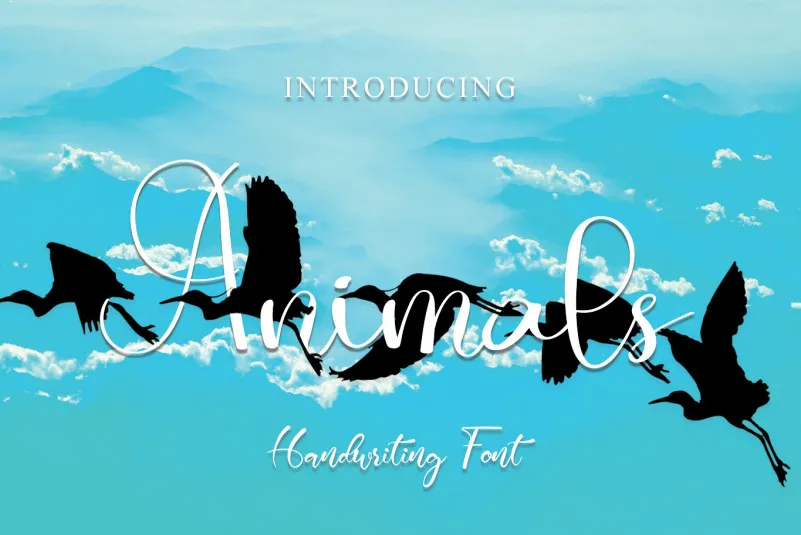
Esta é uma fonte tipo script que se destaca pela sua elegância e detalhe. Ela foi meticulosamente criada para tornar qualquer projeto mais interessante e sofisticado, seja ele um design gráfico, logotipo ou até mesmo um site de notícias. Com este estilo único, você pode adicionar um toque refinado a seus trabalhos digitais, transformando suas criações em verdadeiros obras de arte. Através da ‘Animals Font’, que pertence ao gênero de fontes tipo script e foi criada pelo designer Erik Studio, você encontrará uma opção perfeita para aqueles que buscam um toque elegante e versátil em suas produções digitais.